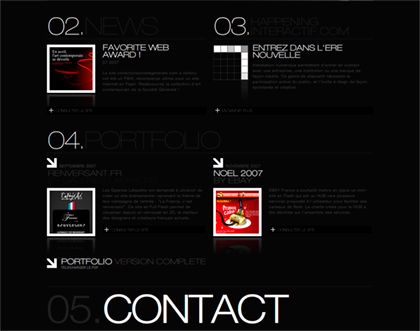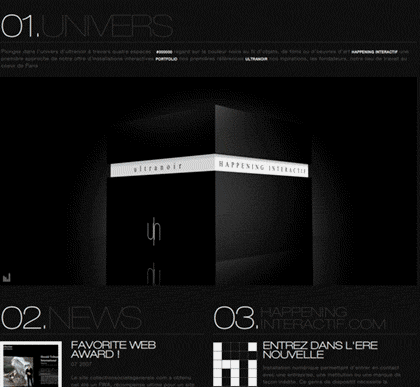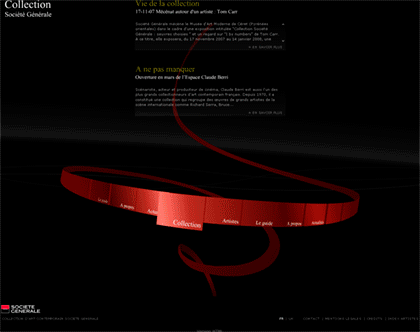
UltraNoir | une webagency de marque
Qui a dit que je n’étais pas sensible au design interactif. Ce serait le comble. Au contraire. Qui a dit que je ne m’interressais qu’au Print… il suffit de se promener sur Design et Typo pour vous convaincre du contraire. J’avoue cependant avoir une nette tendance à aller puiser dans les artistes ‘Old School’ les sensibilités d’hier qui peuvent expliquer voire éclairer celles d’aujourd’hui. Ce que j’aime dans le site d’UltraNoir?
— la mise en page et l’utilisation d’un Noir qui devient élégant grâce à une typographie bien architecturée, simple et lisible
— le design général des animations et
— l’intercativité fluide et très intuitive.
— une navigation simple qui facilite les retours en arrière
— la relative discrétion de l’interface qui n’est là finalement que pour mettre en valeur les artistes exposés
Donc qu’est-ce que je n’aime pas. Peut-être le style très, trop marqué, de notre époque, certaines brillances inutiles et les reflets verticaux qui deviennent vraiment un ‘passage obligé’ du webdesign moderne. Dangereux parce que trop souvent répété. Ça donne une vision un peu kitsch qui ne correspond pas toujours précisément aux artistes en promotion. C’est tout le danger d’une webdesign qui a tendance à tout écraser, avaler sur son passage au travers d’une moulinette de contemporanité.
Picasso qui n’aurait peint que les Demoiselles d’Avignon (centenaire) et qui n’aurait eu de vision que de cubiste tout au long de sa vie. Heureusement non. Et je parie sur les AD d’UltraNoir qu’ils sauront évoluer avec leur époque, voire peut-être la précéder un jour.
Petit détail amusant :
Dans le logo Ultranoir, le filet est plus près du N que du U, pas bien centré !